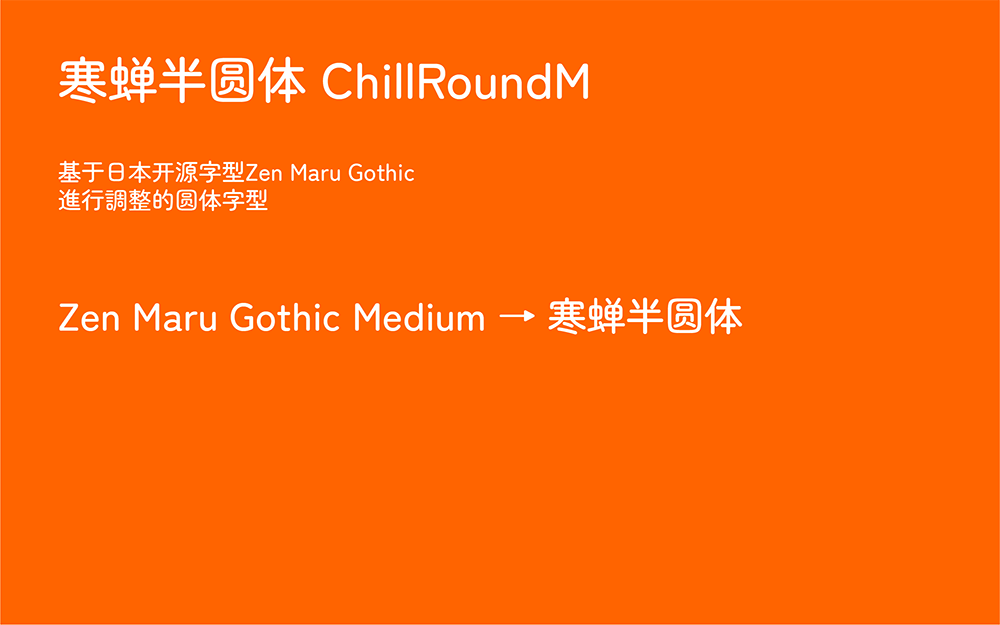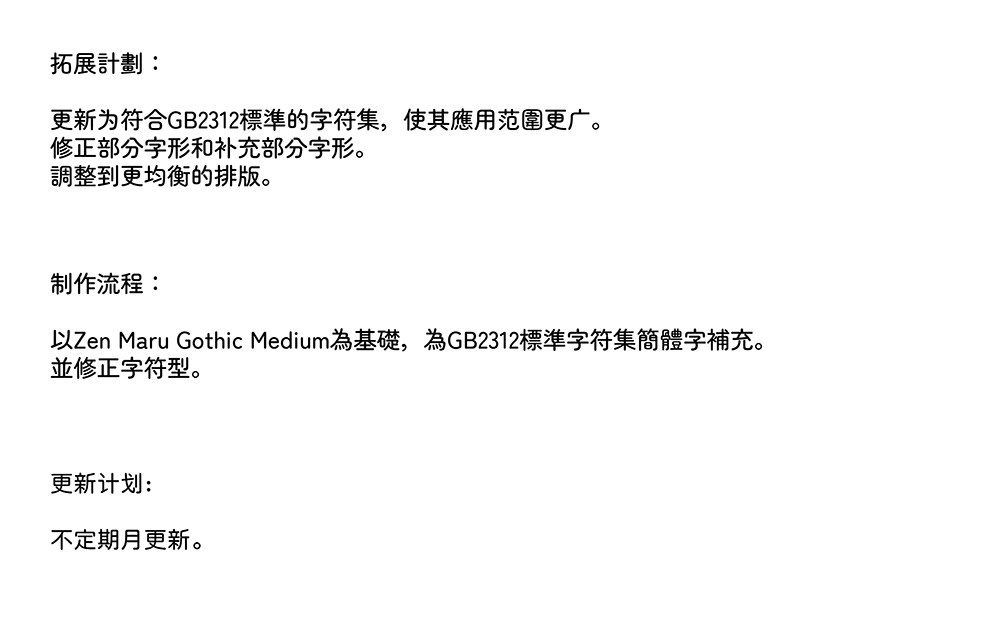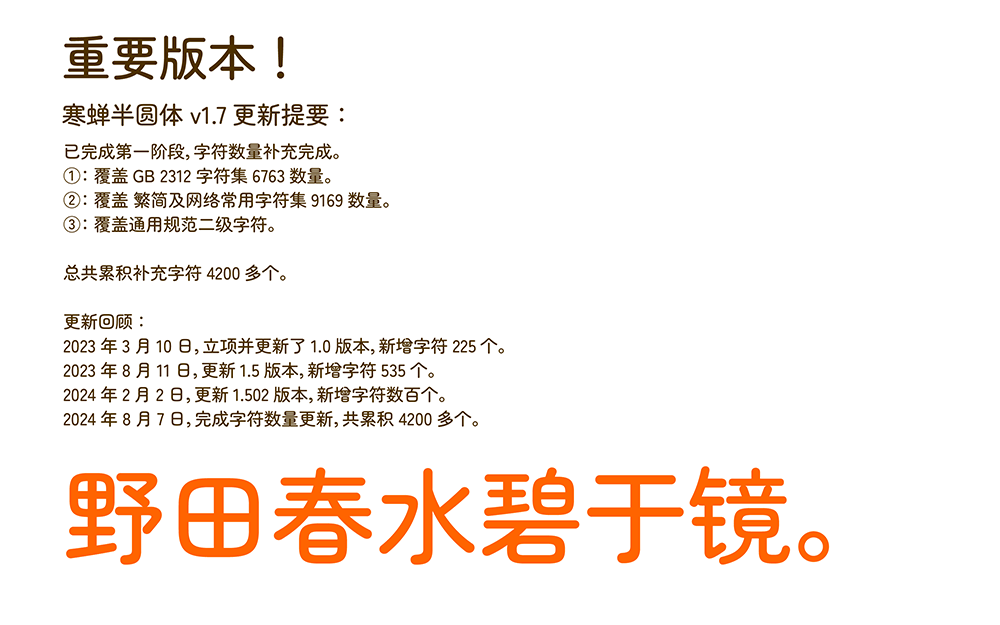
寒蝉半圆体
基于日本开源字型Zen Maru Gothic進行調整的圆体字型!
更新为符合GB2312標準的字符集,使其應用范圍更广。 修正部分字形和补充部分字形。 調整到更均衡的排版。
拓展针割∶
更新为符合GB2312梗华的字符集,使其鹰用范圉更广。修正部分字形和补充部分字形。
稠整到更均衡的排版。
制作流程︰
以Zen Maru Gothic Medium赢基磁,赢GB2312槽潍字符集简醴字捕充。董修正字符型。
更新计划:
不定期月更新。
重要版本!
寒蝉半圆体v1.7更新提要∶已完成第一阶段,字符数量补充完成。①:覆盖GB 2312字符集6763数量。
②:覆盖繁简及网络常用字符集9169数量。③∶覆盖通用规范二级字符。
总共累积补充字符4200多个。
更新回顾∶
2023年3月10日,立项并更新了1.0版本,新增字符225个。2023年8月11日,更新1.5版本,新增字符535个。
2024年2月2日,更新1.502版本,新增字符数百个。2024年8月7日,完成字符数量更新,共累积4200多个。
寒蝉半圆体ChillRoundM v1.800
寒蝉半圆体v1.80(稳定版)更新提要:
①修改字形并添加OpenType替换字符:茎稱曾僧噌增層憎甑繒罾贈蹭赠缯諍錚郛覓奚倩猜睛菁蜻舀滔稻蹈韜爰煖鍰瑶徭埒孚俘孵桴殍蜉綏餒眷豢卷圈绻蜷锩鬈綣錈劵痊筌輇銓聚驟骤鄹刃忍涩紉韌認条條茶搽令伶冷呤囹岭怜拎柃泠玲瓴羚翎聆苓蛉邻铃零领龄鈴領齡簧廣黌氐改灰炭盔黹黻真嗔填慎滇稹缜禛縝鎮顛镇隘縊謚鎰襁碌怦鮃萍角斛桷确觖觚觜觞解觳觴觸奠遒蹲沿船既嘅概禅箪飩飪飫飭餃餉餘餞餡餾饃饅饉饋饌饑饒偐倘徜惝淌绱緔敞耥趟躺逍誚趙銷霄才簪赧化花貨靴虞蜈虎亮珊跚哥歌敢撖澉阚憨橄瞰闞浅残践彪琥號選遷昀逞酲芽迓穿蚜訝雅鴉肓氓望免兔勉娩挽浼冕晚逸鞔毋毎毐毒蚤搔骚瘙鳋騷鰠迢迥迸迹逅逋逑逕逖逡逵逶逾遏遐遑遘遞遨遲遽邀邁邂邃邇邊邏邐素系隧燧摇謡繇鷂博縛薄簿礴哌派蒎旅喝葛褐謁嘴墨黛嚜巷港撰巽庖弥祢称郸婵弹惮掸殚蝉觯冁微媺杀杂馁绥撇鱉斃懊澳燠所拌胖袢絆倦捲惓箞跋祓揄渝瑜觎蝓覦矗
②字形更新:閭營璉褳鏈鰱遣谴缱繾譴,更新部分“辶”相关的字使其更统一。
③字形调整:贷。
④修复字形错误或映射错误:钩 饵 饮 窥窺
Ver 1.750(2024/08/09)
修复“带”映射“帚”的错误。
新增汉字字符232个,共计字符数12430。
优化了“辶”相关字形。
重新设计了“丽”相关字符。
多一些对汉字的支持。
Ver 1.70(2024/08/07)
已完成第一阶段,字符数量补充完成。
覆盖 GB 2312 字符集6763 数量。
覆盖繁简及网络常用字符集 9169 数量。
覆盖通用规范二级字符。
总共累积补充字符 4200 多个,总字符12198。